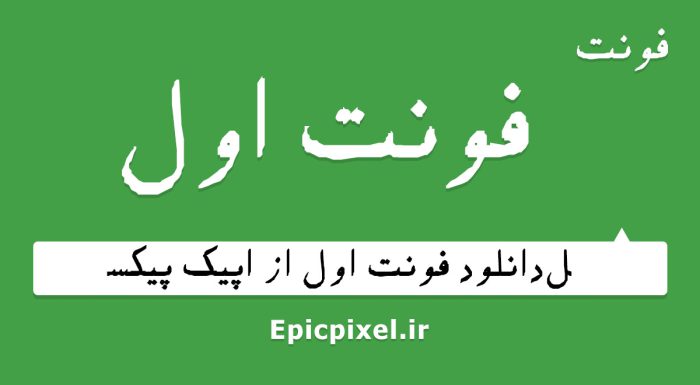
فونت اول فارسی Aval
فونت اول یک فونت بهم ریخته و شلخته مخصوص برنامه فارسی ساز ( این فونت نیاز به برنامه فارسی ساز دارد از سری F )
در غیر اینصورت توجه کنید عکس مربوط به پست با همین فونت نوشته شده به فارسی
شبیه اونایی هست که رو تخته سیاه میخواستیم بنویسیم